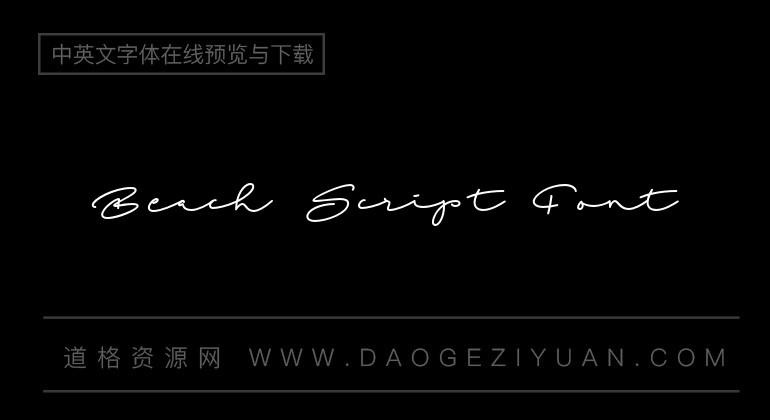
Beach Script Font
Beach Script是一种手写风格的字体,其风格轻松、自然,适合用于海滩、度假、夏季风格的设计项目。这种字体的特点是字母之间有很大的间距,字母笔画没有完全闭合,以及许多字母的笔画都带有弧度,使整个字体看起来更加流畅。 Beach Script字体包括大写字母、小写字母、数字和标点符号,可以用于各种设计项目,如海滩旅游海报、度假杂志、海滩餐厅菜单等等。该字体呈现出一种轻松、舒适、欢快的感觉,可以让你的设计看起来更加有趣和吸引人。
Beach Script Font是一款非常不错的手写艺术字体,具有很好的视觉感,适合于文化类的宣传设计、商业类品牌的广告和产品包装设计以及个性化文字排版等较多场景。